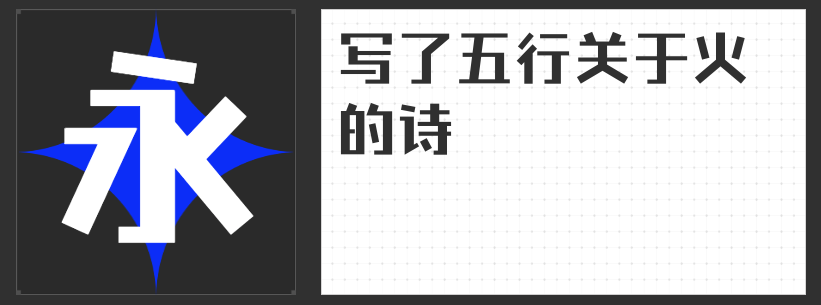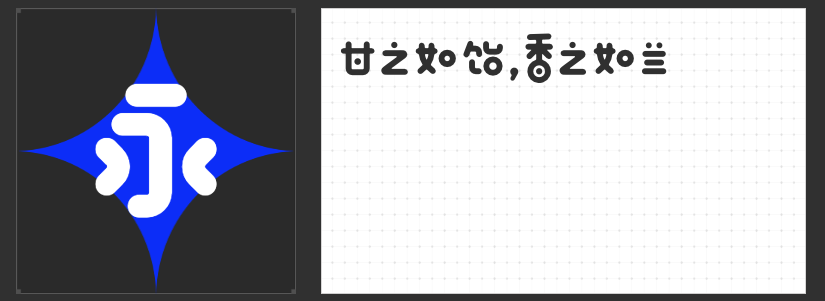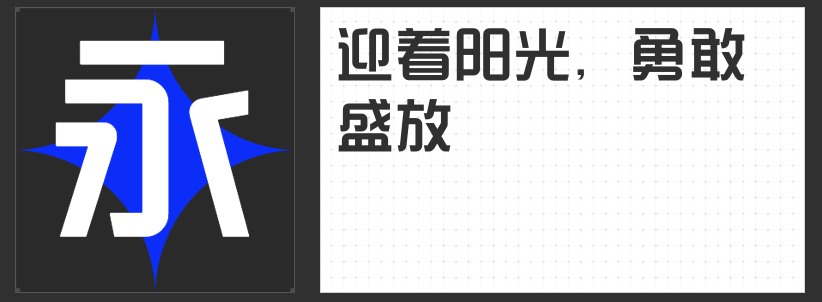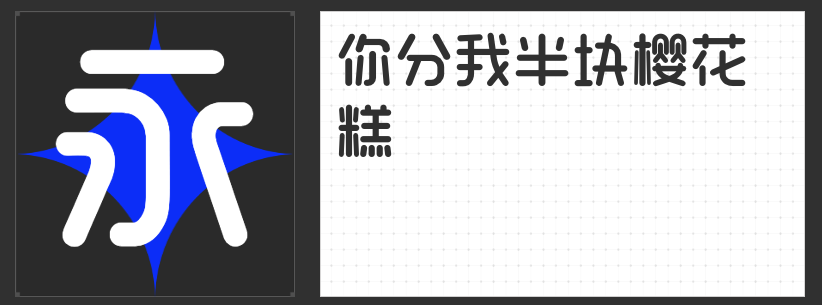
海报设计四款宝藏字体推荐:从灵动创意到锋芒个性
在海报设计的视觉叙事中,字体不仅是信息传递的载体,更是情绪与风格的直接表达。一款契合主题的字体,能瞬间点燃观众注意力,强化品牌记忆点。本文精选四款各具特色的创意字体,从圆润可爱到锋利现代,满足不同场景下的设计需求。
一、创客贴综艺体常规
这款字体以黑体为骨架,却通过独特的圆弧处理打破传统黑体的生硬感。笔画转折处采用流畅的弧线衔接,既保留了黑体的简洁清晰,又赋予字体柔和的亲和力。在需要平衡专业感与活力的设计中,它既能传递稳重的信息,又通过细节处的圆润设计增添一丝灵动,适合科技、教育、生活类海报的标题或副标题,让文字在理性中透出温度。
二、创客贴幼稚园体
如果说综艺体是“轻熟的优雅”,那么创客贴幼稚园体则是“童真的绽放”。这款字体将所有笔画进行极致圆润处理,转折处如气球般饱满,整体风格可爱到溢出屏幕。它的设计语言直击人心,无需复杂装饰即可营造出轻松愉悦的氛围,尤其适合母婴、儿童、文创类海报,或需要传递温暖、欢乐情绪的场景。圆润的笔画自带“无攻击性”的视觉信号,能快速拉近与观众的距离。
三、励字钧线黑简 大黑
当设计需要传递力量感与决断力时,励字钧线黑简 大黑是绝佳选择。这款字体以完美的斜度与利落的转折构建视觉张力,棱角分明的设计摒弃了过度装饰,却通过细节优化(如笔画粗细的微妙变化)降低阅读障碍,兼顾个性与实用性。全直线的设计语言符合当代极简审美,能瞬间成为画面焦点,适合运动、汽车、科技类海报,或需要强调品牌态度的场景,用“锐利”的视觉语言征服观众。
四、创客贴软糖体
如果传统字体的规整让你感到束缚,软糖体则是打破常规的创意利器。它采用相同粗度的线条绘制,却通过字框宽度的灵活变化,让每个字在同等字号下拥有独特的宽高比例。这种设计为排版提供了无限可能——设计师可以自由调整字间距、行间距,甚至让文字与图形产生互动,营造出充满呼吸感的视觉效果。它适合艺术、音乐、潮流类海报,或需要突出设计感的场景,让文字成为画面中的“动态元素”。
从综艺体的灵动、幼稚园体的可爱,到钧线黑的锋利、软糖体的自由,这四款字体以截然不同的设计语言,为海报设计提供了丰富的表达维度。无论是传递温暖情绪、强化品牌态度,还是突破排版常规,它们都能成为你创意工具箱中的“秘密武器”。